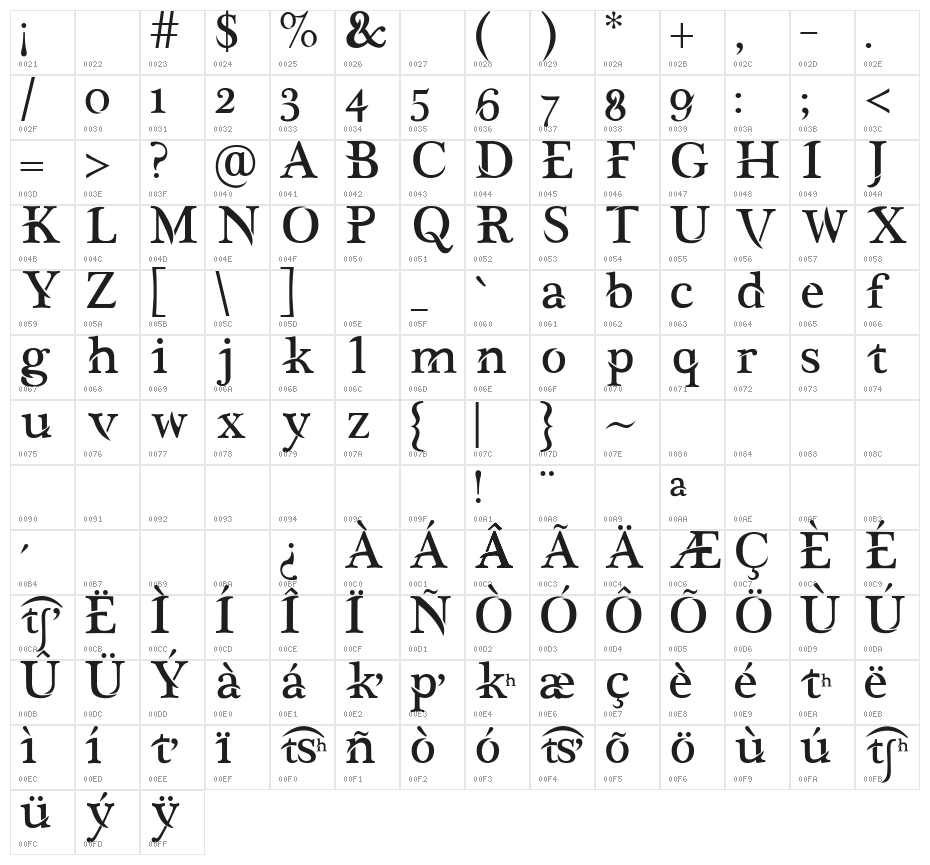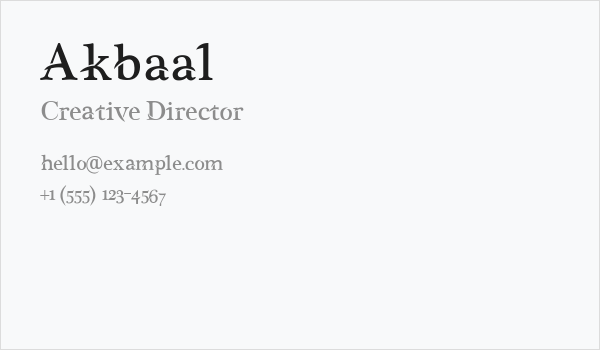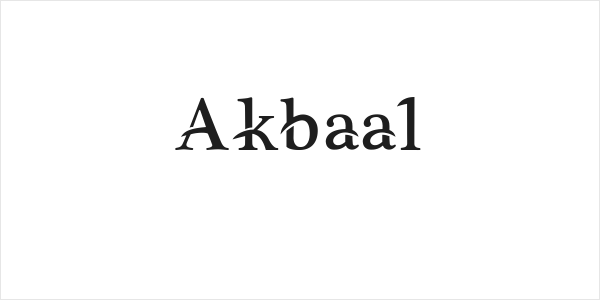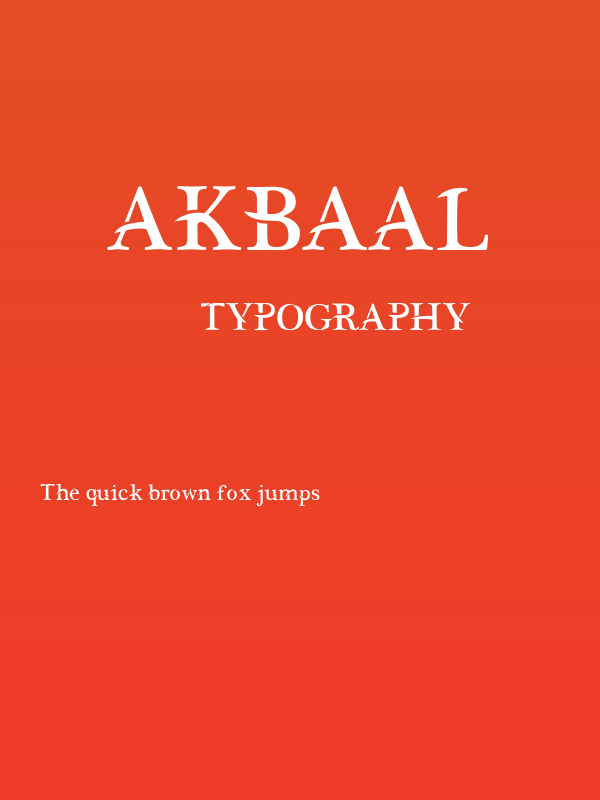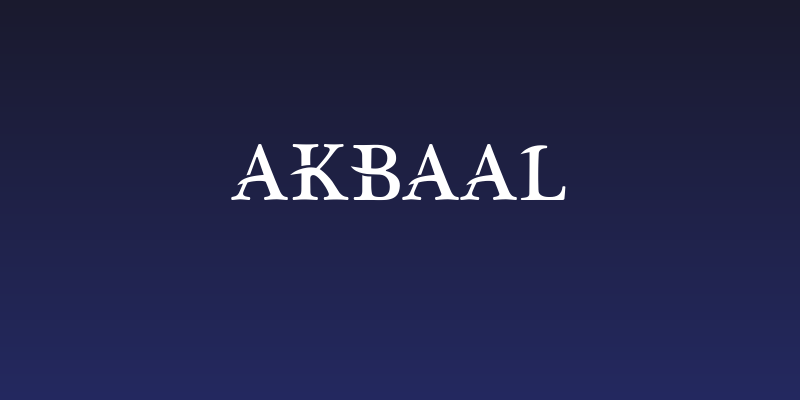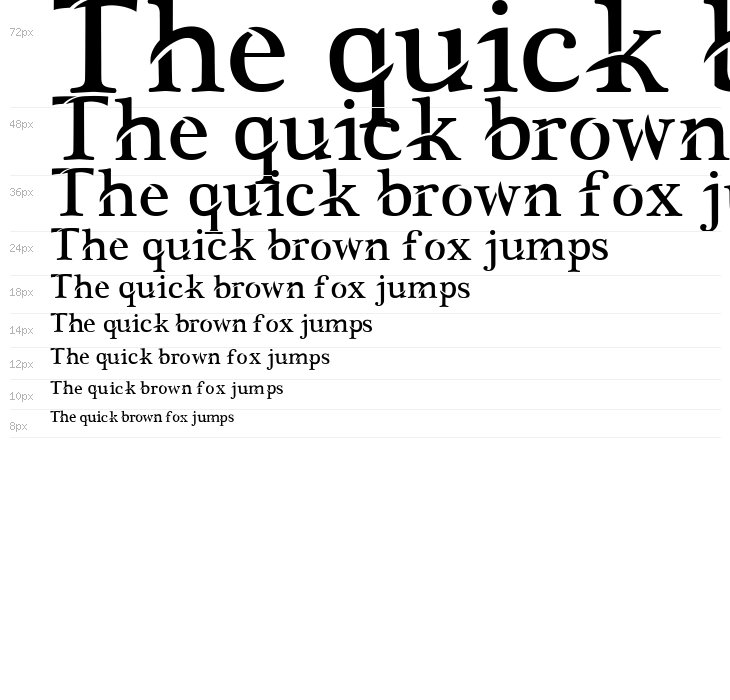
Akbaal Font
| Gesamtstil | Classic |
| Anwendungsfall | Headlines, Logos, Editorial design |
| Vorgeschlagene Projekte | Ideal for book covers, editorial design, branding, and luxury product packaging. |